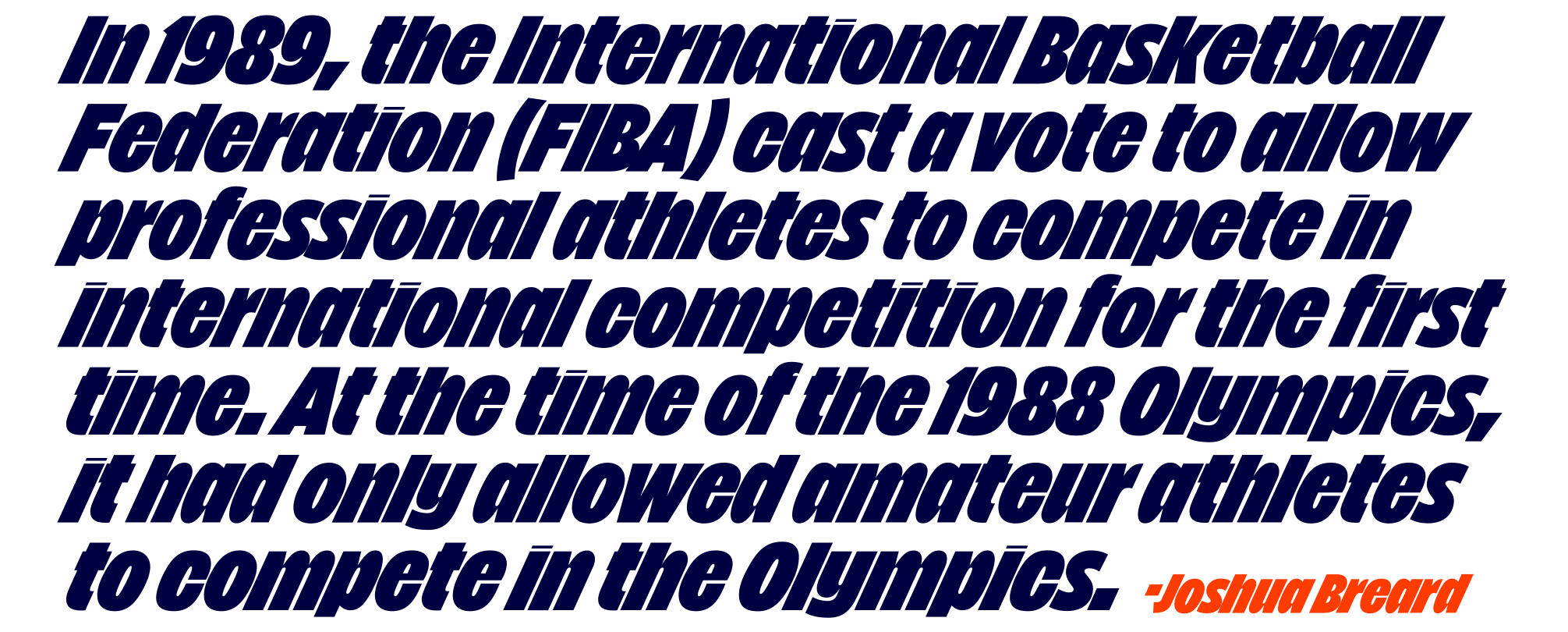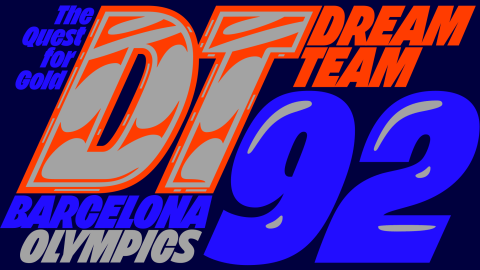
BRZO là kiểu chữ hiển thị 5 phong cách lấy cảm hứng từ sự táo bạo của đồ họa bóng rổ những năm 90. Khi lớn lên, căn phòng của tôi tràn ngập các áp phích của Dream Team, thẻ giao dịch Fleer và danh mục Eastbay. 20 năm sau, thời đại đầy ảnh hưởng này đã biểu hiện thành một kiểu chữ sans serif in nghiêng toàn thân muốn một chiếc áo đấu được may vào. Khoảng cách giữa các chữ cái có chủ ý chặt chẽ của BRZO mang lại cho dòng tiêu đề một điểm nhấn bổ sung. Xếp chồng nó, đặt nó theo đường chéo hoặc sử dụng bóng đổ… bất kể dịp nào BRZO sẵn sàng chơi.